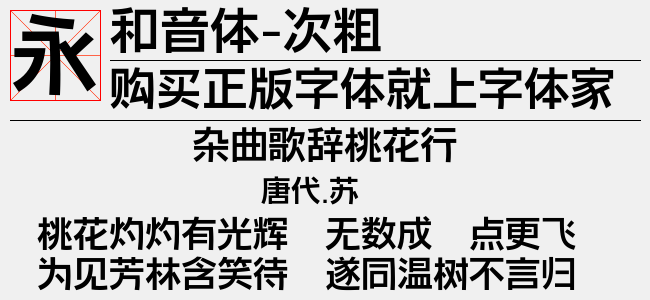
和音体-次粗 字体大小955.84 K,包含了6763个汉字以及附加其他英文字体和阿拉伯数字,属于极字和风字库。和音体-次粗(TTF)可以免费下载,商业用途请自行购买版权,它的特征就是创意,标题,广告,印刷,采用安装嵌入的安装方式,支持符号拉丁文日文中文等语言
字体作者:极字和风字库
字体名称:和音体-次粗